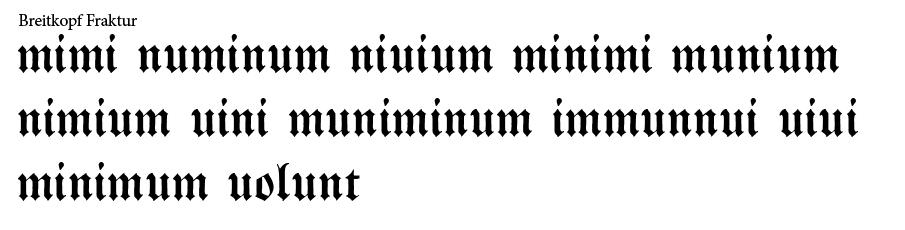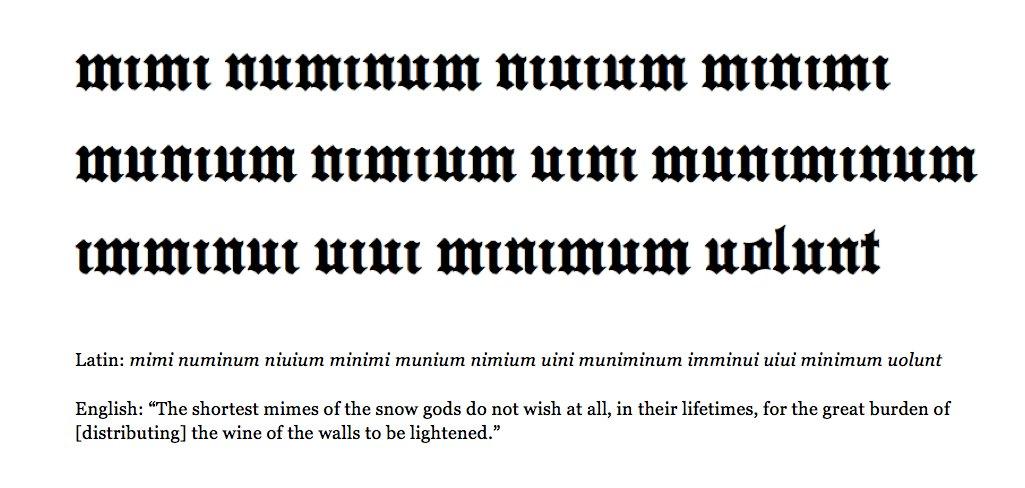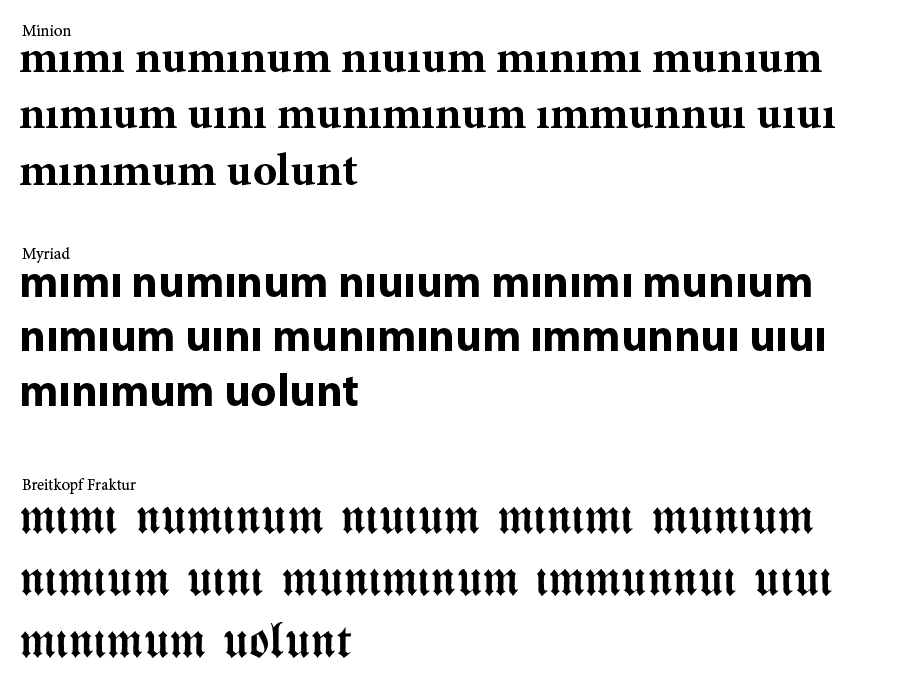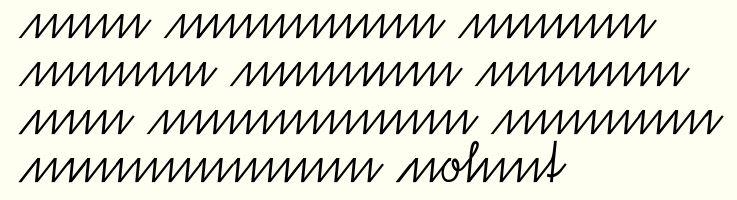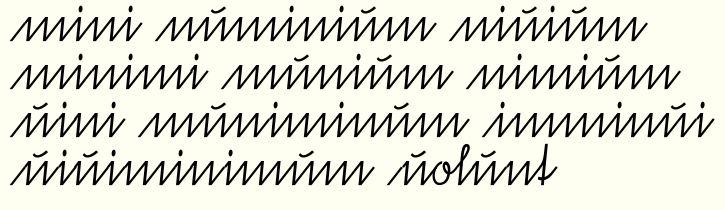
Zur Ehrenrettung: Die fehlenden i-Punkte erschweren das Lesen zusätzlich, auch in anderen Schrifttypen …
Das lässt sich mit Kurrent noch toppen. Wahrscheinlich ist das der Grund für die Erfindung des i-Punktes und des Häkchens über dem u. Ohne den i-Punkt und das u-Häkchen säh das so aus:
Ich mag mir gar nicht vorstellen, wie das im Diktat endet, wenn man jetzt an der richtigen Stelle die i-Punkte und u-Häkchen setzen soll...
Wahrscheinlich ist das der Grund für die Erfindung des i-Punktes und des Häkchens über dem u.
...und vermutlich auch dafür, dass U und V überhaupt getrennte Wege gingen.
Weiß eigentlich jemand genau, wann u und v eindeutig den Graphemen /u/ und /f/ zugeordnet wurden, denn zu Dürers Zeit waren ja u und v stellungsabhängige Allographen für jeweils beide Grapheme, also ähnlich wie ſ und s, nur irgendwie Spiegelverkehrt, v am Wortanfang und nach einer Wortfuge, u im Wortinneren und am Wortende.
Nicht leicht zu lesen.
Kann gar nicht sein, Fraktur ist doch die leserlichste aller ... ach nee, ist ja kein ſ an irgendeiner Fuge ...
Weiß eigentlich jemand genau, wann u und v eindeutig den Graphemen /u/ und /f/ zugeordnet wurden, denn zu Dürers Zeit waren ja u und v stellungsabhängige Allographen für jeweils beide Grapheme, also ähnlich wie ſ und s, nur irgendwie Spiegelverkehrt, v am Wortanfang und nach einer Wortfuge, u im Wortinneren und am Wortende.
Wobei das auch immer mal wechselte und stellenweise frei kombinierbar war. Wie die meisten Merkmale "nichtmittelalterlicher"  Orthographie geht auch Unterscheidung von u und v als phonetische auf das 16. Jahrhundert zurück. (etwa bei Schottel(ius) oder von Zesen)
zum eigentlichen Thema: Ein mittelalterlicher Schreiber (und die Fraktur geht ja auf Schreibschriften zurück), hätte den ganzen Text eher wie folgt geschrieben:
Kann gar nicht sein, Fraktur ist doch die leserlichste aller ... ach nee, ist ja kein ſ an irgendeiner Fuge ...
Die gebrochenen Schriften waren ja auch nicht dazu entwickelt, besonders leserlich, sondern besonders platzsparend zu sein. :-D
Der Dozent meines universitären Paläographie-Kurses. Gut, „sie wurden dazu entwickelt“ ist etwas übertrieben ausgedrückt, da auch andere Faktoren (z.B. Schreibgeschwindigkeit) die Entwicklung beeinflussen.
Zur Begründung der Aussage: Die gebrochenen Schriften wurden in einer Zeit entwickelt, in der Beschreibstoff noch teuer war (vier Quartseiten Pergament kosten nunmal ein Schaf+Arbeitsaufwand, Papier kam erst später auf und konnte noch später erst zu Preisen produziert werden, die so große Verbesserung aufweisen konnte, dass das Papier tatsächlich allgemein erschwinglich und „verschwendbar“ war), wobei gleichzeitig immer mehr Personengruppen Interesse an Büchern hatten (am Anfang, d.h. im Frühmittelalter, hatten eigentlich nur kirchlich/klösterliche Einrichtungen Bücher, später kamen erst Höfe, dann städtische Eliten hinzu), sodass der Preis immer mehr eine Rolle spielte. Und der kann (bei feststehender Textmenge und Beschreibstoff) nur gesenkt werden, indem der Platz stärker ausgenutzt wird, dies zeigt auch die Entwicklung:
Zum Vergleich: Bibel-Handschriften des 9. Jahrhunderts(noch kaum gebrochen), des 12. Jahrhunderts und des 13. Jahrhunderts.
Diese Platzersparnis wird im Wesentlichen durch drei Faktoren erreicht:
1. Die Verringerung von Abständen, ins Besondere am Rand, aber auch zwischen den Zeilen und Buchstaben.
2. Die Verwendung von Ligaturen Abbreviaturen, letztere habe ich versucht, in meinem Beispiel zu simulieren, in dem Beispieltext ist eine starke Verkürzung jedoch nicht möglich, da die Wörter entweder zu selten oder zu kurz sind, um „Ganz-Wort-Abbreviaturen“ auszubilden. Während die Ligaturen bis in den modernen Satz erhalten blieben, finden sich die Abbreviaturen nur noch in frühen Drucken, etwa in der Gutenberg-Bibel. (vgl. quē für quem (Z.1, Mitte) und dicim⁹ für dicimus (Z.2, Ende) in der folgenden Seite
3. Die Entwicklung von Schriften mit geringerer Laufweite. Kann man in den oben gelisteten Beispielen zeigen, findet sich aber auch in der Literatur, so bei Kapr/Schäfer: Fotosatzschriften. Leipzig 1989 (S. 144) über die Lutherische Fraktur: „In Bezug auf die Papierökonomie überflügelt sie mühelos alle Antiquaschriften, was ihr aber als Vertreter der nahezu in Vergessenheit geratenen gebrochenen Schriften wenig Dank einträgt.“
Hierzu tragen auch Schaftbrechungen bei (ein Bogen „verbraucht” mehr Platz als eine schräge Linie, wie man sehen kann, wenn man e und e bzw. n und n bei gleicher Schriftgröße vergleicht).
Gleichzeitig führt diese Entwicklung zu einer schlechteren Lesbarkeit (vgl. etwa das diskutierte Beispiel, aber auch das folgende Zitat: „Bei der Gestaltung [der textura formata]  hatte die künstlerisch-graphische Wirkung Vorrang vor der bequemen Lesbarkeit. Die klare Unterscheidbarkeit der Buchstaben wurde der ästhetischen Gleichförmigkeit untergeordnet. Dies betraf vor allem die Buchstaben n, m, u und i, die in Textura formata schwer zu unterscheiden sind, wenn sie hintereinander stehen, aber auch e und c.“ (Quelle: Wikipedia).
⁵ eigene Erfahrung und Gespräche mit Fachkräften.
⁶ „Einen wichtigen Anteil am Aufkommen der Kursive als Buchschrift hate nicht zuletzt die Einführung des Papiers als neuer, gegenüber dem bisherigen  Pergament billigerer Schreibstoff“ (Schneider, S. 58) „Daß aber die Wahl von Kursive oder Textualis auch vom Beschreibstoff abhing, beweisen etwa gleichzeitige Exemplare des oberbayerischen Landrechts auf Pergament, für die die Textualis alks Schriftart gewählt wurde [während die Papierfassung in einer Kuriven geschrieben wurde]“ (ebd. S. 60, Fußnote 109.)